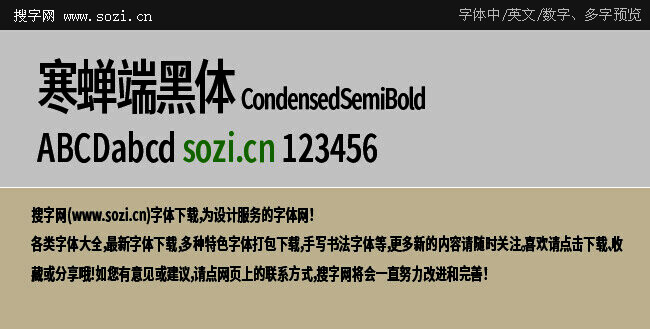
寒蟬端黑體CondensedSemiBold
搜字網(wǎng)給大家提供一款寒蟬端黑體CondensedSemiBold中文字體下載,寒蟬端黑體是基于思源黑體進(jìn)行調(diào)整的黑體字體,在原字體風(fēng)格上重新插值生成,Condensed系列的寒蟬端黑體是思源黑體的長體版本。適用于標(biāo)題設(shè)計、海報設(shè)計、書籍排版以及網(wǎng)頁設(shè)計等應(yīng)用。